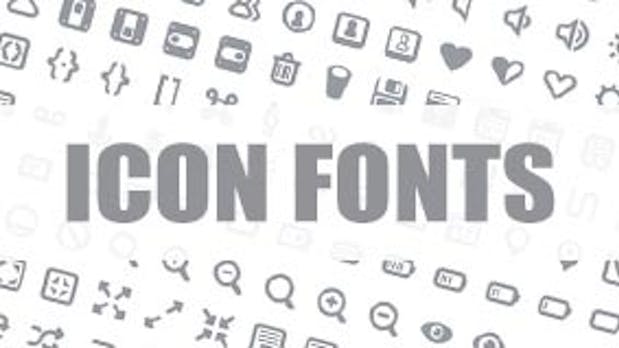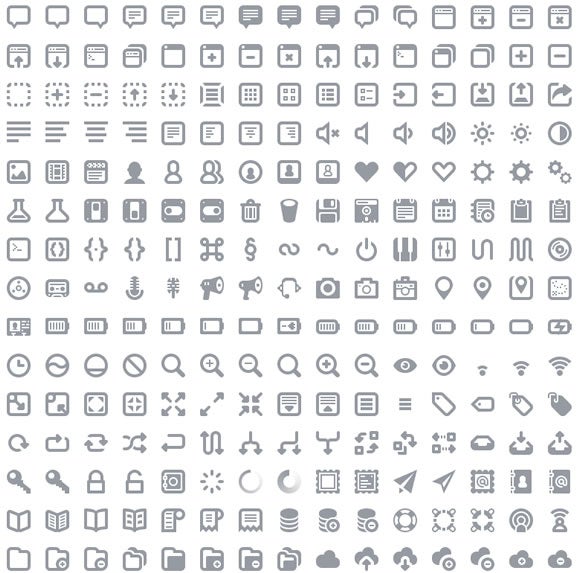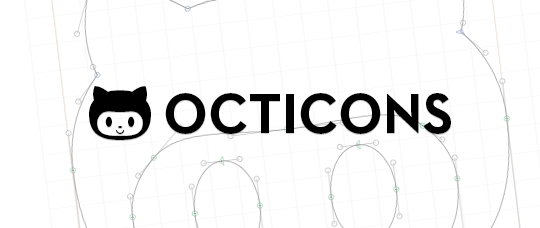
Icon-Fonts: 12 kostenlose Schriftarten für dein Projekt
Icon-Fonts sind toll, denn wie der Name schon sagt, handelt es sich hierbei um Schriftarten und nicht um Bilder, was ihnen eine ganze Reihe von Vorteilen gegenüber klassischen Icon-Implementationen verschafft. So kann man zum Beispiel ohne große Umstände die Farbe im CSS ändern, während man sonst ein Bildbearbeitungsprogramm bemühen müsste. Auch die Skalierbarkeit oder das Hinzufügen von Effekten sind bei Icon-Bildern stark limitiert.
Damit ihr gleich loslegen könnt, haben wir zwölf nützliche und kostenlose Icon-Fonts für euch zusammengestellt:
MFG Labs
MFG-Lab ist ein Icon-Set, das ursprünglich für ein internes Projekt entwickelt wurde. Das Set ist Retina Ready, wird konstant erweitert und verwendet einen eigenen Satz von Unicode-Codes um Überschneidungen mit anderen Zeichen, anderer Fonts zu vermeiden. Auf der Offiziellen Seite vom MFG Labs Icon Set erfährst du mehr.
Entypo
Entypo ist ein Set von mehr als 250 Piktogrammen als OpenType, TrueType für den Desktop-Einsatz und über @font-face nutzbare Formate. Auf der Webseite von Entypo erfährst du mehr über den unter Creative Commons Lizenz stehenden Font.
Ligature
Ligature ist ein kostenloser Icon-Font unter der SIL-Open-Font-Lizenz des Designers Kazuyuki Motoyama. Das Set enthält über 240 Icons und steht auf der offiziellen Webseite von Ligature zum Download zur Verfügung.
Linecons
Linecons Free ist ein Set von 48 Vektor-Icons im Outline-Stil für die Erstellung von Web- und mobilen Interfaces. Das Set steht kostenlos – auch für kommerzielle Zwecke – in verschiedenen Schrift- und Grafikformaten bei Designmodo zum Download zur Verfügung.
Elusive Icons
Der Elusive-Icons-Webfont wurde aus der Not heraus erstellt, einen nicht mit Lizenzen belasteten Font für den Einsatz in Web-Projekten zu finden. Das Resultat sind 283 kleine Piktogramme, die sich gut in fast jedes Design einfügen können. Mehr zum Font erfährst du im offiziellen GitHub Repository von Elusive Icons.
Brandico
Brandico ist ein durch Crowdsourcing entstandener Font von bekannten Logos wie verschiedenen Social Networks, Messengern und vielem mehr. Der Font steht unter der Creative-Commons-Lizenz und im GitHub Repository von Brandico zum Download zur Verfügung.
Batch
Batch besteht aus über 300 Piktogrammen im PSD-, SVG-, PNG- und Webfont-Format. Den kostenlosen Icon-Font kannst du auf der offiziellen Webseite des Batch-Icon-Fonts herunterladen.
Modern Pictograms
Moden Pictogramms Pro ist eine Erweiterung des ehemals kostenlosen Icon-Font-Sets Modern Pictogramms. Der Font wurde komplett überarbeitet und um 130 zusätzliche Icons erweitert. Auf der Offiziellen Webseite von Modernpictograms ist der Font für 25 US-Dollar erhältlich.
Typicons
Typicons enthält über 300 Icons für fast jede Lebenslage. Das Set wurde vor Kurzem um 220 neue Icons ergänzt und steht kostenlos auf der offiziellen Seite zum Download zur Verfügung.
Iconic Icon Set
Iconic ist ein kostenloser Open-Source-Icon-Font mit über 170 minimalistischen Icons, die streng nach einem eigenen Gestaltungsraster aufgebaut sind. Den Icon-Font als PNG, SVG, TTF, EOT und in anderen Formaten erhältst du auf der offiziellen Seite von Iconic.
Octicons
Octicons ist eine Icon-Font von den Machern von GitHub. Bei der Erstellung der Schrift ging das Designer-Team unkonventionelle Wege: Statt die Icons direkt im Vektorprogramm zu entwerfen, begann das Team die Layouts in Photoshop. So konnte von vornherein sichergestellt werden, dass die Icons in den von GitHub benötigten Größen (16 und 32 Pixel) perfekt funktionieren. Selbstverständlich ist der Font im Endeffekt trotzdem vektorisiert worden, sodass er auch in anderen Größen gut funktioniert. Den fast 180-Zeichen starken Icon-Font findet ihr auf der offiziellen GitHub Seite von Octicons.
Font Awesome
Font Awesome ist speziell für Bootstrap entwickelt worden. Die Schriftart besteht aus rund 360 Icons, verträgt sich gut mit Screen Reader Software, funktioniert im Internet Explorer 7 und ist kostenlos auf der Projektseite von Font Awesome verfügbar.
Webfont Icons sind klasse und ich habe sie auch schon mehrmals eingesetzt.
Ein toller Dienst ist auch die Webseite http://www.fontello.com.
Dort sind die meisten hier aufgeführten Fonts ebenfalls verfügbar und man kann sich die gewünschten Icons aussuchen und daraus eine neue Font (inkl. CSS etc.) erstellen lassen.
Der Vorteil ist, dass man nicht alle Fonts laden muss, Speicher und auch Ladezeiten einspart.
Ich benutze immer http://fortawesome.github.com/Font-Awesome/ die haben echt ne Menge Icons. Zudem kann auch eine eigene abgespeckte Version erstellt werden.